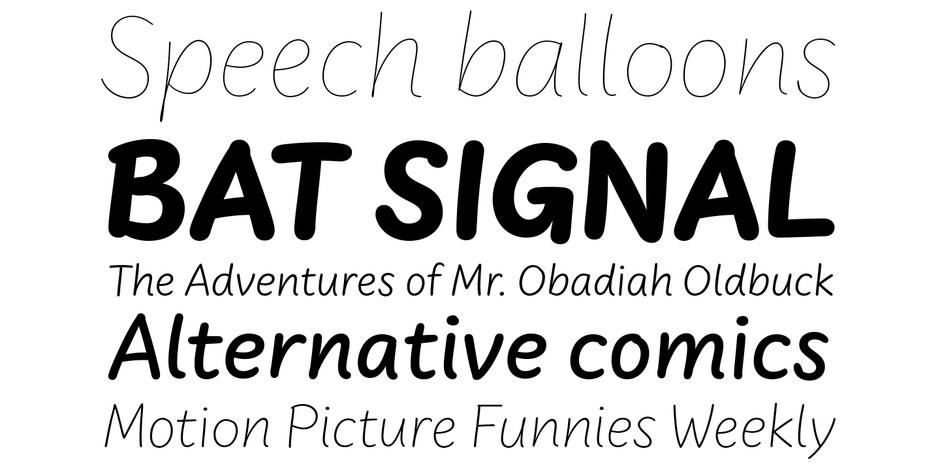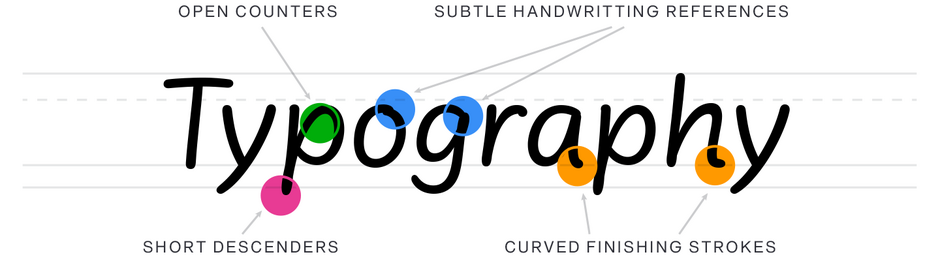
FF Uberhand™ Font Field Guide
GIESSEREI: FontFont
DESIGNER: Jens Kutilek
KLASSIFIZIERUNG: Casual Handwriting Script
BESTE PRAXIS
Sparsam verwenden, in informellen Kontexten, für Kindermaterialien oder zwanglose Kommunikation. Vermeiden Sie professionelle Dokumente, achten Sie auf die Lesbarkeit und stellen Sie sicher, dass die Schrift die Designästhetik ergänzt.
FAMILIE
Die Uberhand-Text-Familie besteht aus zwei Schriftschnitten, Regular und Bold, deren Abstände und Farben für längere Texte auf Papier oder Bildschirm abgestimmt sind. Die 11 vielseitigen Schnitte von Hairline bis Black der Headline-Familie, genannt FF Uberhand, sind Display-Designs mit engeren Abständen und weniger unregelmäßigen Zeichen.
FONT FACTS
- Die Schriftart Regular der FF Uberhand Text-Familie enthält auch viele Icons, Dingbats und Symbole.
- FF Uberhand Text ist eine lebendigere Version der Schrift mit großzügigeren Abständen. Sie ist in Größen von 6-16 Punkt auf Papier und auf dem Bildschirm zu Hause.
ROOTS
Nach mehreren fehlgeschlagenen Versuchen, die Buchstaben zu zeichnen, wurde Kutilek klar, dass die beste und effektivste Methode darin bestand, mit einem Stifttablett direkt im Font-Editor zu schreiben. Anschließend verschob er diese groben Formen in die Hintergrundebene und zeichnete sie komplett neu, um genau das gewünschte Aussehen zu erzielen.
LEGIBILITÄT
Nicht für Bücher oder lange Texte geeignet, ist Uberhand eine lebendige, aber präzise gezeichnete Schrift. Sie ist bei praktisch jeder Größe gleichbleibend gut.